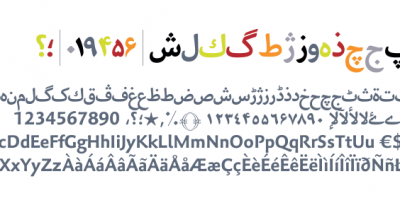
اشراق
قلم زیبای اشراق با پشتیبانی از زبان های عربی و فارسی فونت زیبا در ۵ وزن می باشد. این فونت مناسب کلیه کارهای پوستر سازی و طراحی و حتی استفاده در وب می باشد. ظاهر کلی فونت براساس فونت کوفی می باشد.